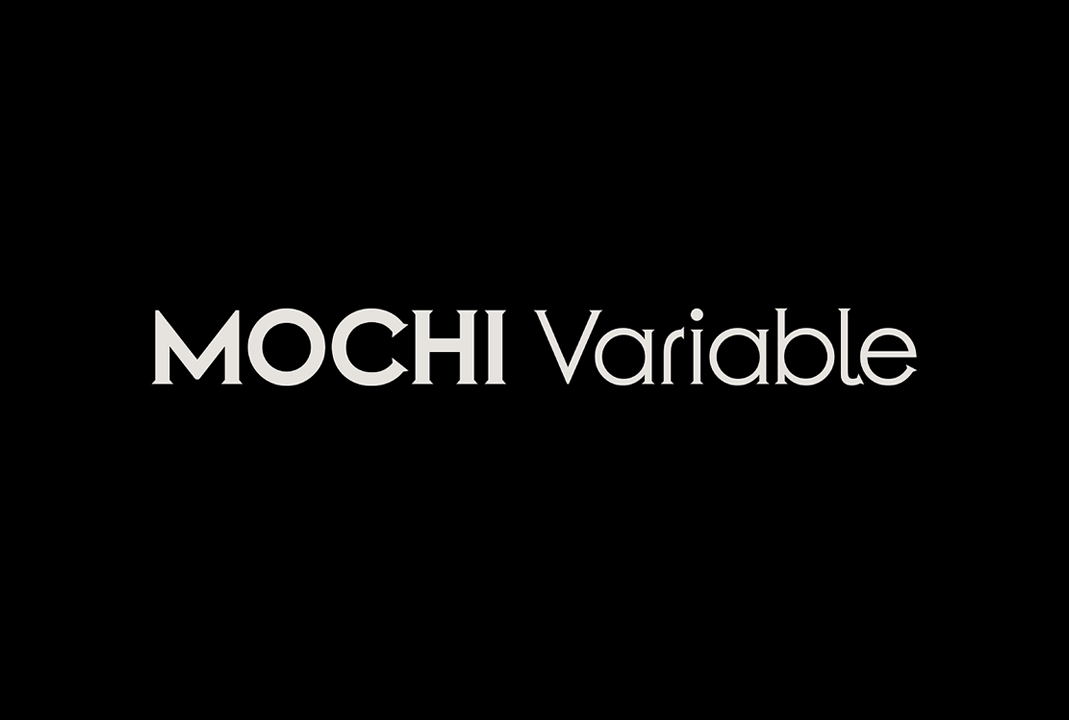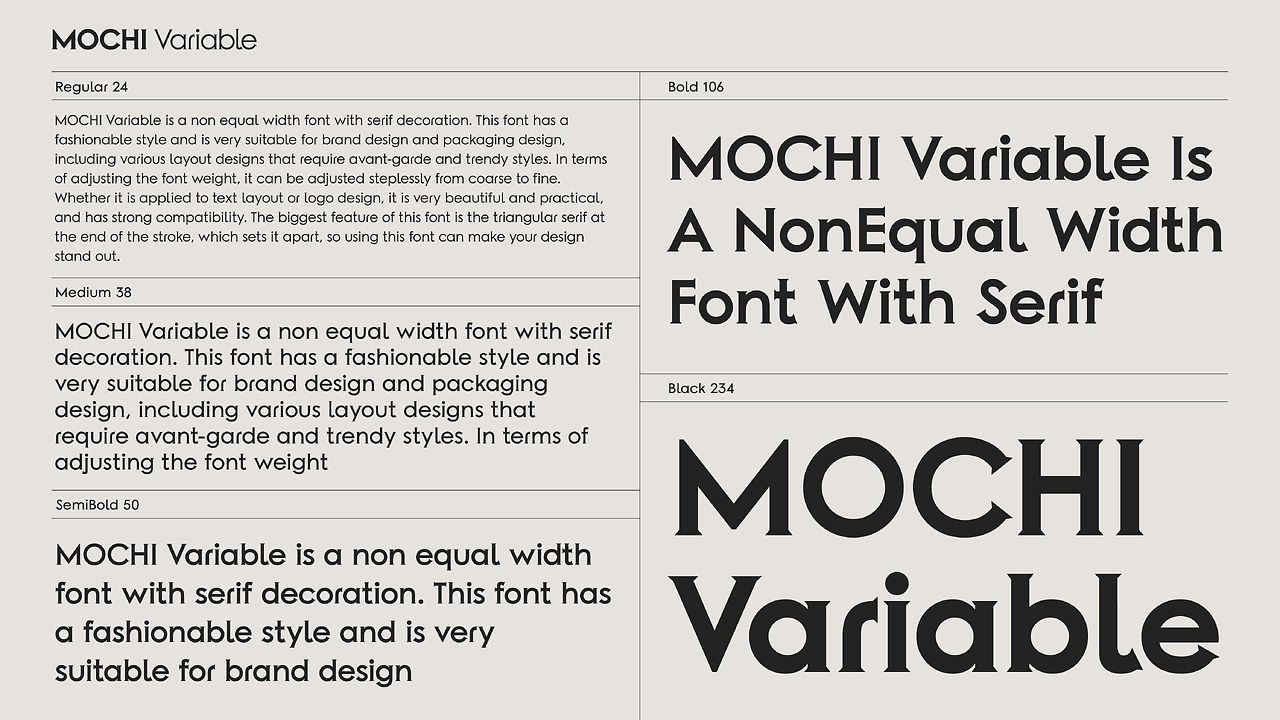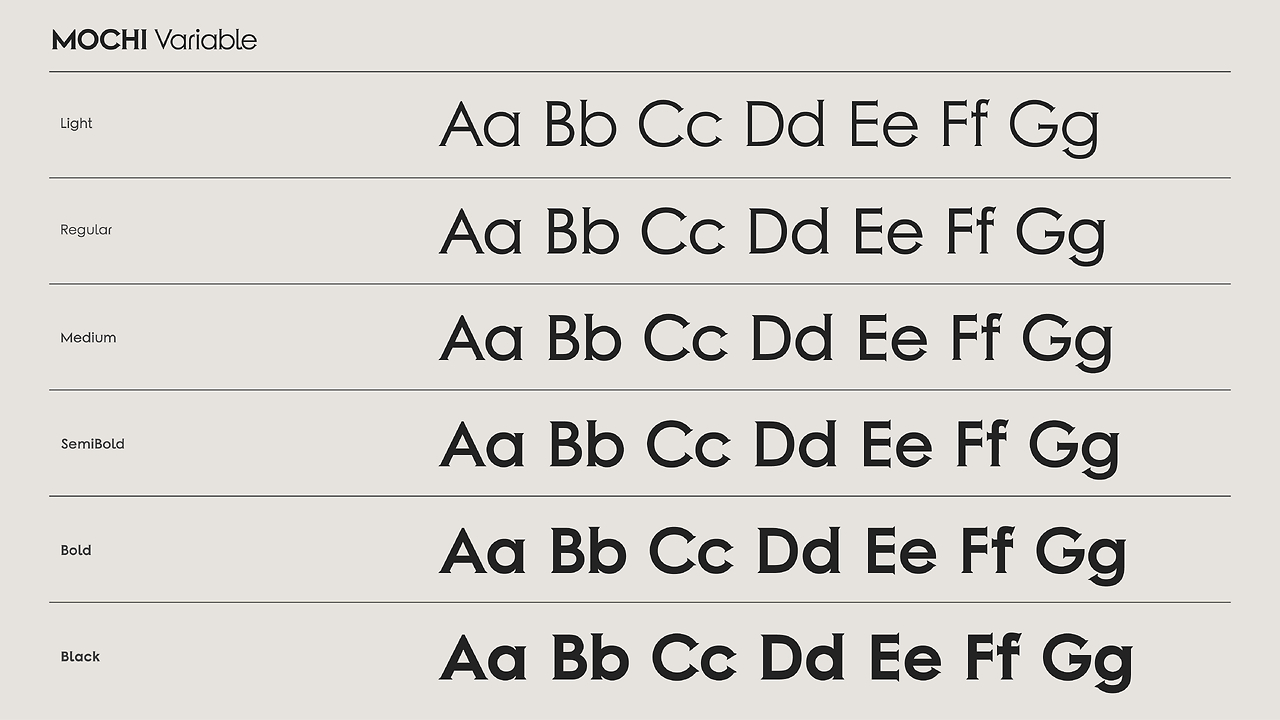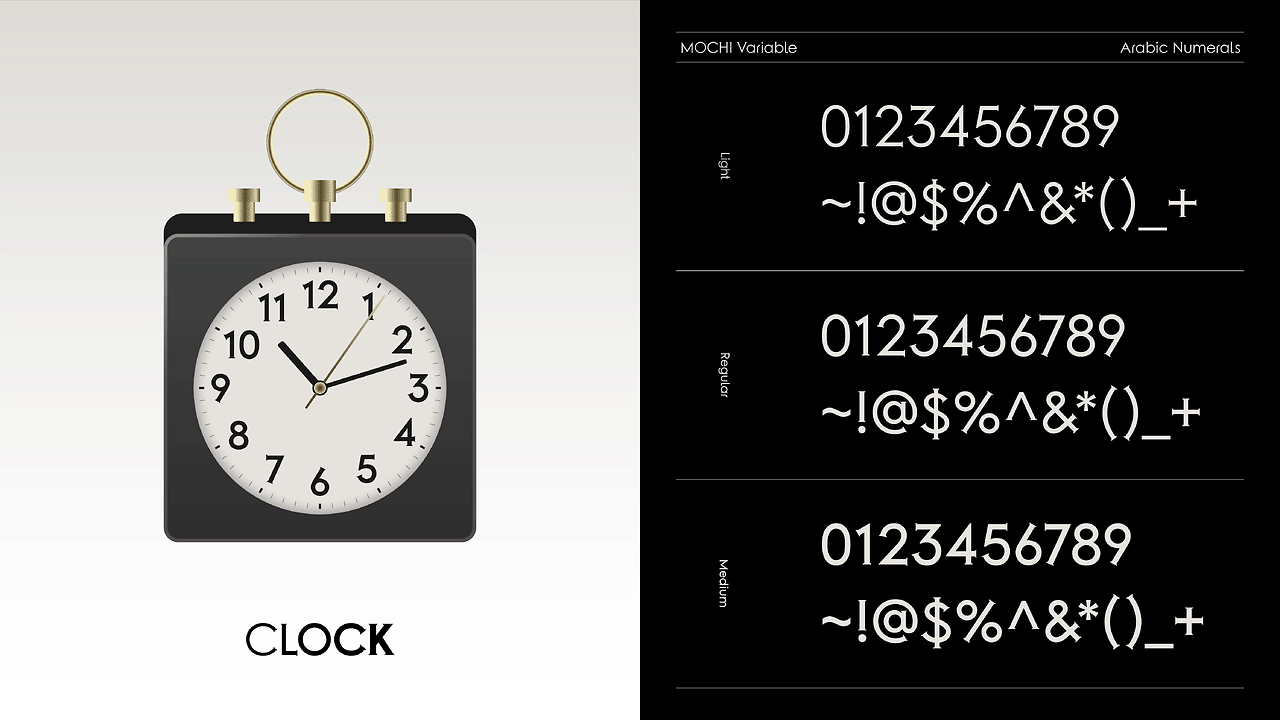
MOCHI Variable 免费商用可变英文字体下载
MOCHI Variable 是由站酷网友(UID:17198304)发布的一款免费商用可变英文字体,该字体风格来源于 Copperplate Gothic,笔画末端有微小的衬线装饰,该风格字型已经有百年历史,即前卫,又能保留复古庄重的氛围感,这是一个在衬线与无衬线之间的好选择。